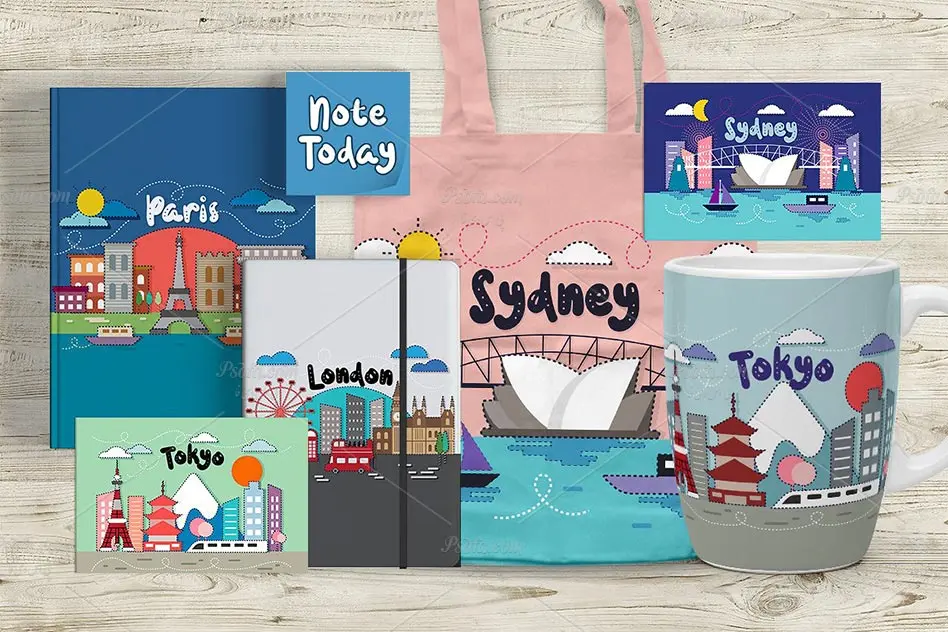
فونت دستنویس انگلیسی و فانتزی Travelogue
در این مطلب شاهد فونت دستنویس انگلیسی و فانتزی Travelogue مناسب جهت استفاده در طراحی و گرافیک می باشید. این فونت زیبا در قالب 4 فایل ttf و otf در سایت قرار گرفته است که با نصب این مجوعه فونت در پوشه فونت های سیستم قادر به استفاده مستقیم از آن ها در تمام نرم افزارهای گرافیکی و ویرایشگر متن از جمله نرم افزار فتوشاپ ، مجموعه نرم افزار آفیس و … می باشید. این فونت در 4 سبک مختلف طراحی شده است که بر حسب نیاز می توانید از هر کدام استفاده کنید. از این فونت زیبا می توان در طراحی بر روی انواع پارچه و لباس ، طراحی بر روی بسته بندی محصولات ، طراحی بر روی ظروف سلولزی ، طراحی انواع پوستر و … استفاده نمود.
- طراحی در 4 سبک مختلف